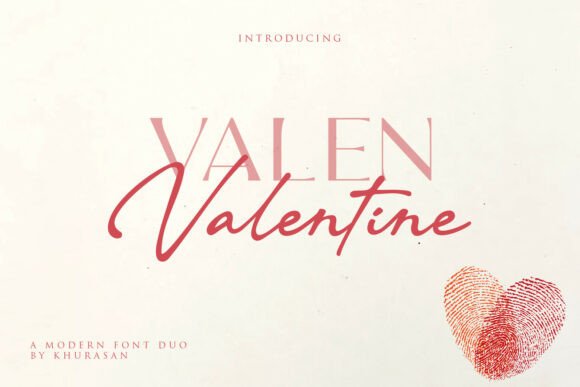
Valen Valentine Duo
Valen Valentine Duo – A Fonte Romântica que Encanta Corações
Se você busca a combinação perfeita entre emoção e elegância para seus projetos, Valen Valentine Duo é a escolha ideal. Esta família tipográfica reúne um script fluido, reminiscentemente das cartas de amor manuscritas, e um serif moderno e limpo, proporcionando equilíbrio visual e legibilidade.
Por que Valen Valentine se destaca?
- Dupla harmoniosa: o script delicado traz a sensação de intimidade, enquanto o serif garante clareza e profissionalismo.
- Versatilidade criativa: perfeita para convites de casamento, cartões de Dia dos Namorados, branding romântico, citações nas redes sociais e embalagens temáticas.
- Impacto emocional: a tipografia transmite paixão instantânea, conectando o leitor ao sentimento da mensagem.
- Compatibilidade total: funciona bem em impressão de alta resolução e em telas digitais, mantendo nitidez em qualquer tamanho.
- Facilidade de uso: inclui estilos de peso que permitem variações sutis sem perder a identidade da fonte.
Aplicações práticas que brilham com Valen Valentine
Ao usar Valen Valentine Duo, você pode transformar simples projetos em verdadeiras declarações de amor:
- Convites de casamento: o script faz o nome dos noivos parecer escrito à mão, enquanto o serif organiza detalhes como data e local.
- Cartões de Valentine's Day: crie mensagens que parecem tiradas de um diário secreto.
- Branding de marcas de luxo: a combinação transmite sofisticação sem perder a proximidade emocional.
- Posts de mídia social: destaque citações românticas com tipografia que prende o olhar.
- Embalagens temáticas: adicione um toque de charme a produtos como chocolates, velas e joias.
Valen Valentine Duo entrega exatamente o que promete: calor, intimidade e elegância. Seja para projetos pessoais ou para clientes exigentes, esta fonte garante que cada palavra carregue uma história de amor inesquecível. Não perca a oportunidade de elevar seu design a um novo patamar de romance e sofisticação.